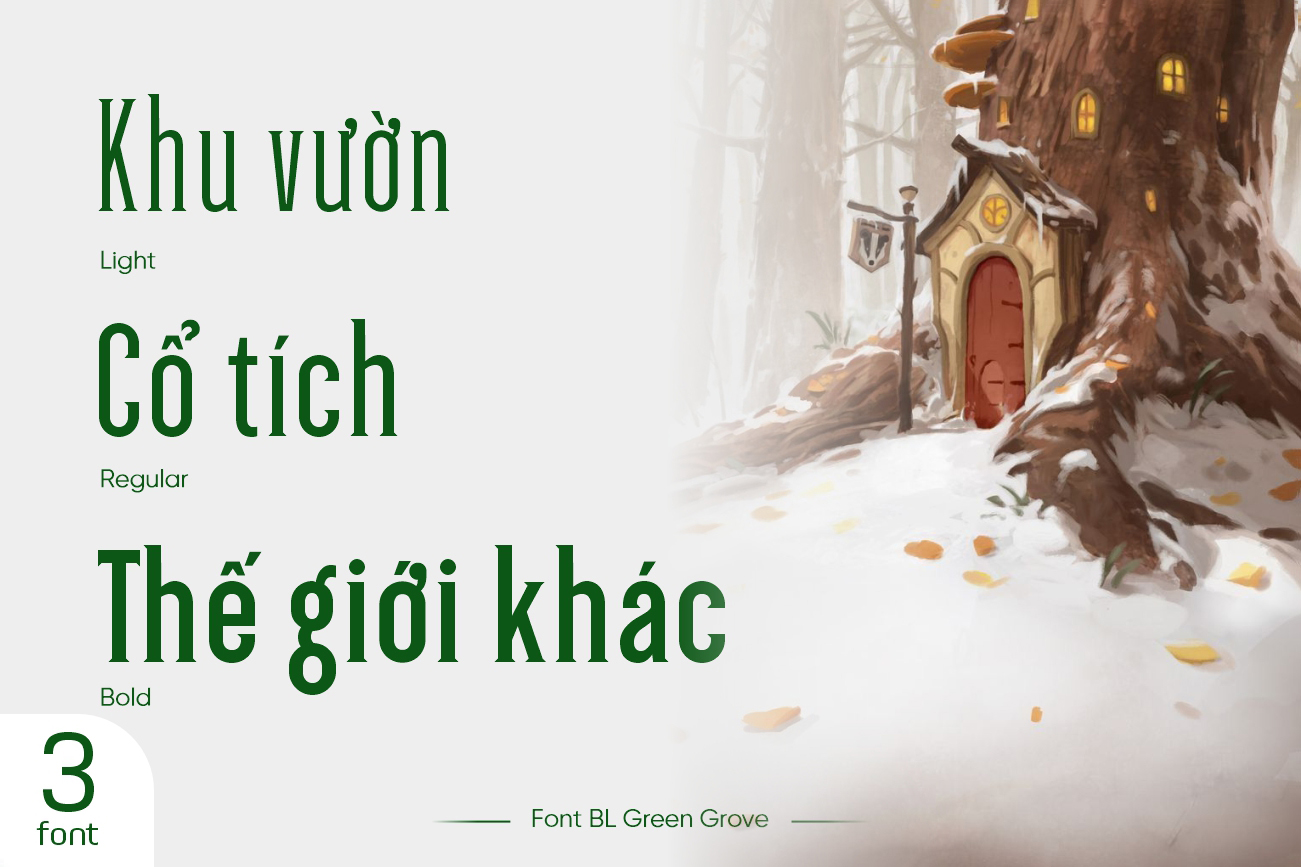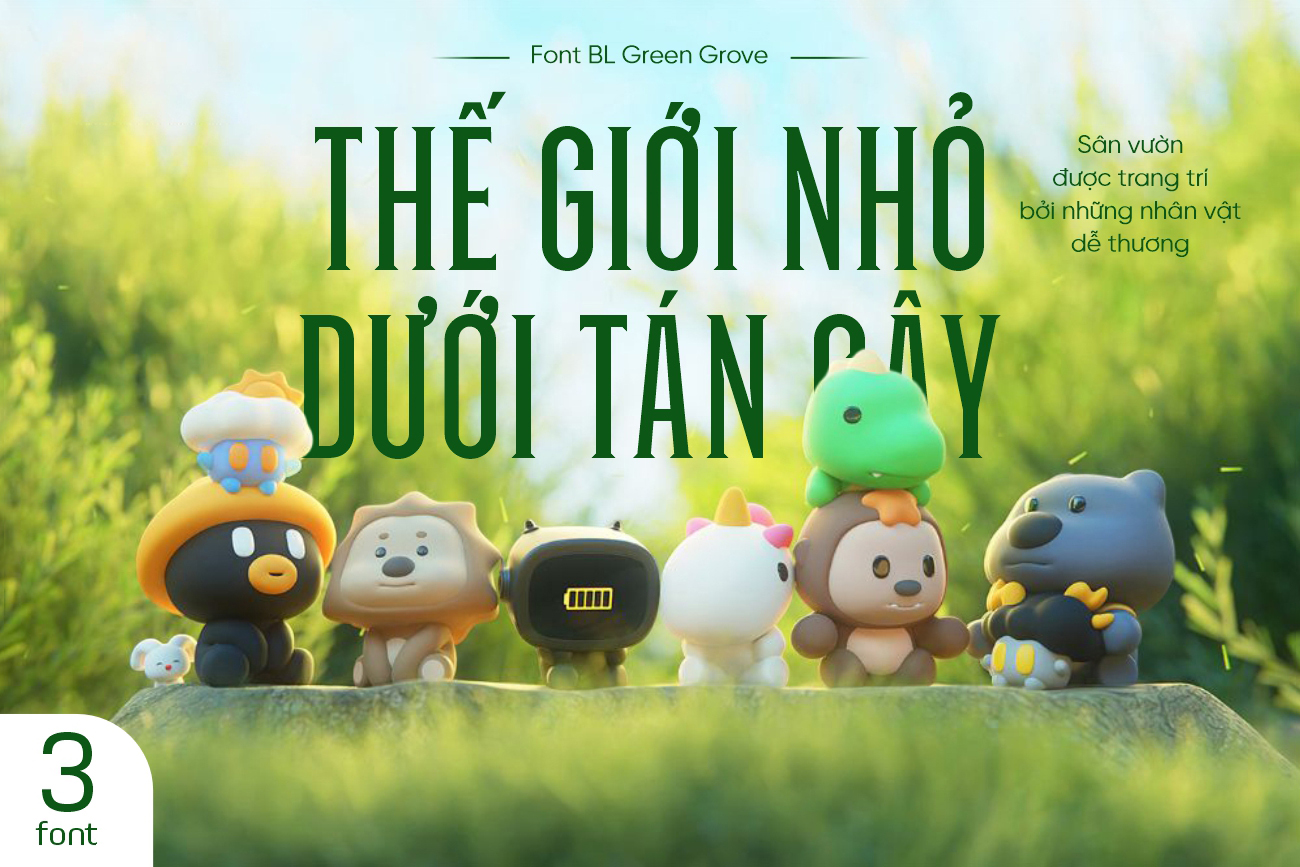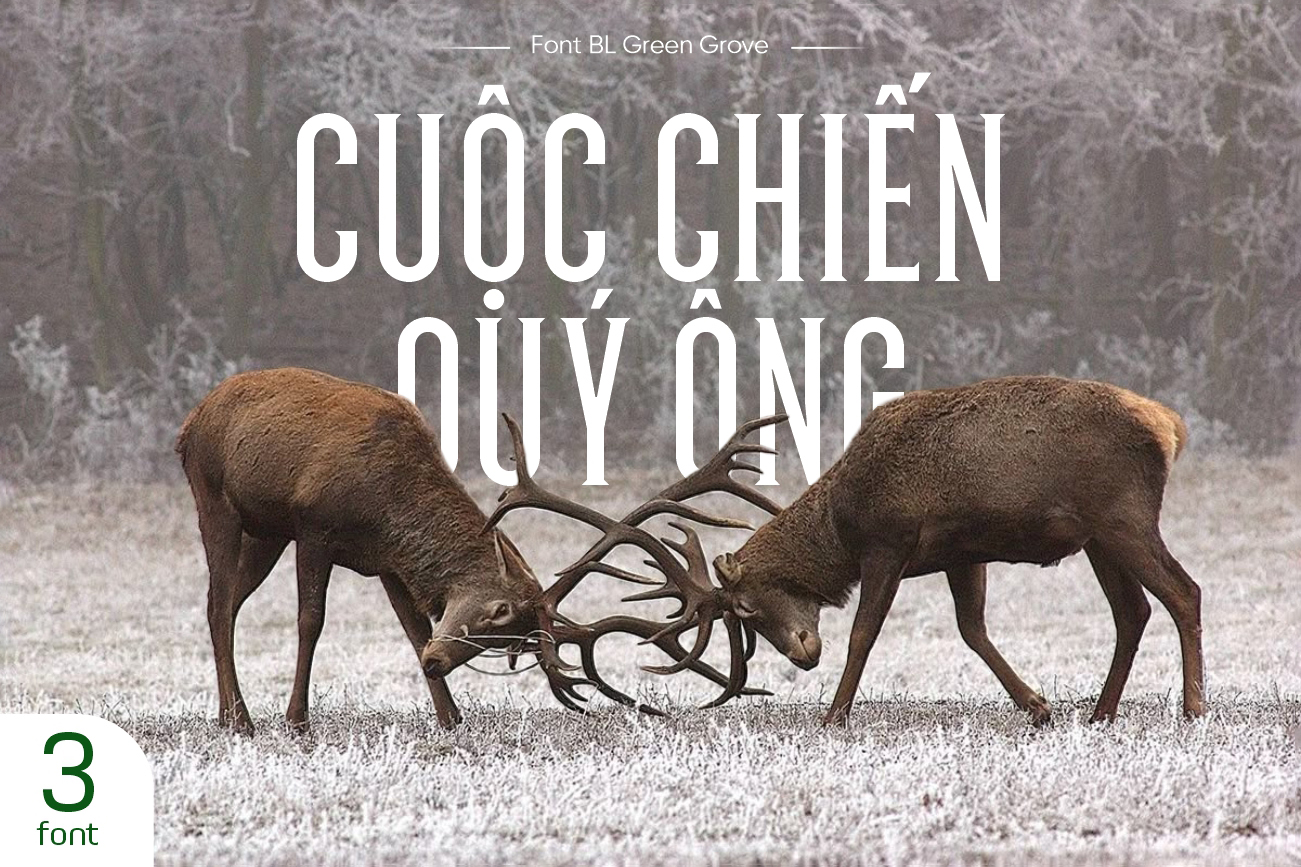
Phông chữ Việt hóa BL Green Grove
Tác giả Sergey Godovalov
Việt hóa Font BL
BL Green Grove là phiên bản Việt hóa từ bộ font Green Grove do Sergey Godovalov thiết kế, mang phong cách vừa cổ điển vừa đậm chất hiện đại, tạo nên một diện mạo độc đáo và đầy chiều sâu thị giác. Đây là một font serif gothic hiện đại, mang trong mình tinh thần mạnh mẽ nhưng vẫn được xử lý khéo léo để trở nên thanh lịch, sang trọng, phù hợp với nhiều dạng thiết kế khác nhau. Ngay từ cái nhìn đầu tiên, BL Green Grove tạo ấn tượng bởi cấu trúc chữ sắc nét, các chi tiết serif được làm sắc sảo nhưng không quá cứng, vừa gợi cảm giác quyền lực, vừa đem lại nét tinh tế rất đặc trưng.
Phiên bản Việt hóa do Team BL thực hiện đảm bảo hiển thị tiếng Việt trọn vẹn, dấu đẹp, cân bằng bố cục ký tự, giúp font phát huy tối đa giá trị thẩm mỹ trong môi trường thiết kế Việt Nam. Gồm 3 độ dày chữ: Light, Regular, Bold cho các yêu cầu trình bày khác nhau như tựa đề, nội dung ...
Về kiểu dáng, BL Green Grove sở hữu những chi tiết chữ có phần dày dặn, mạnh mẽ nhưng vẫn giữ được sự mềm mại nhất định nhờ sự tinh chỉnh tỉ mỉ trong từng đường nét. Tinh thần gothic được biểu đạt rõ rệt qua cảm giác huyền bí, quyền lực, nhưng lại được kết hợp khéo léo với phong cách thời thượng, khiến bộ chữ trở thành mẫu font serif gothic hiện đại đúng nghĩa. Nhờ đó, BL Green Grove không chỉ tạo cảm giác cổ điển mạnh mẽ mà còn toát lên sự thanh lịch, sang trọng, phù hợp để sử dụng trong các poster cao cấp, thiết kế thời trang, bìa sách, quảng cáo cao cấp, tạp chí, branding hoặc các dự án sáng tạo cần sự ấn tượng và đẳng cấp ngay từ phần chữ.
Nguồn gốc cảm hứng của Green Grove đến từ tinh thần gothic pha lẫn hơi thở thiết kế đương đại, nơi truyền thống và hiện đại giao thoa để tạo nên một bộ chữ mang bản sắc riêng. Khi được Team BL Việt hóa thành BL Green Grove, bộ font không chỉ giữ nguyên sự mạnh mẽ, nghệ thuật của phiên bản gốc mà còn trở nên thân thiện hơn với người dùng Việt nhờ khả năng hiển thị tiếng Việt hoàn hảo.
Nếu bạn đang tìm một bộ chữ kết hợp hài hòa giữa cổ điển và hiện đại, mang đúng tinh thần font serif gothic hiện đại, đồng thời vẫn đủ thanh lịch, sang trọng để nâng tầm thiết kế, thì BL Green Grove chắc chắn sẽ là lựa chọn đáng giá, giúp nội dung trở nên ấn tượng, khác biệt và đầy chiều sâu cảm xúc.